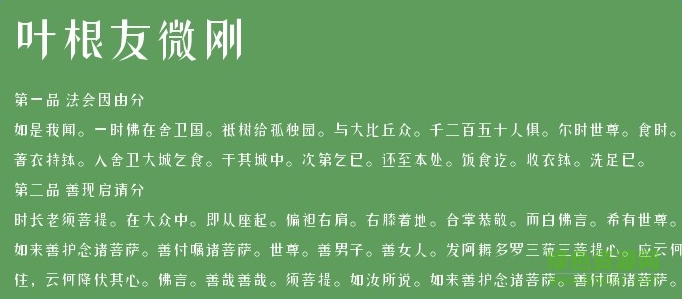
葉根友微剛體字體是一款非常漂亮的電腦字體,這款字體簡(jiǎn)單大方而有銳氣,整體效果比較清新耐看,喜歡這款字體的朋友可以來(lái)綠色資源網(wǎng)下載體驗(yàn)喲!
該字體風(fēng)格獨(dú)特,設(shè)計(jì)的理念來(lái)自竹林里砍竹子后的斜切面創(chuàng)意,利用這個(gè)創(chuàng)意應(yīng)用在書(shū)法字體上,形成了較好的體現(xiàn)效果。在2016年發(fā)布的這么多字體中,小編最喜歡的就是這款字體了,很獨(dú)特的視覺(jué)沖擊效果,讓人一看就過(guò)目不忘這樣的字型。